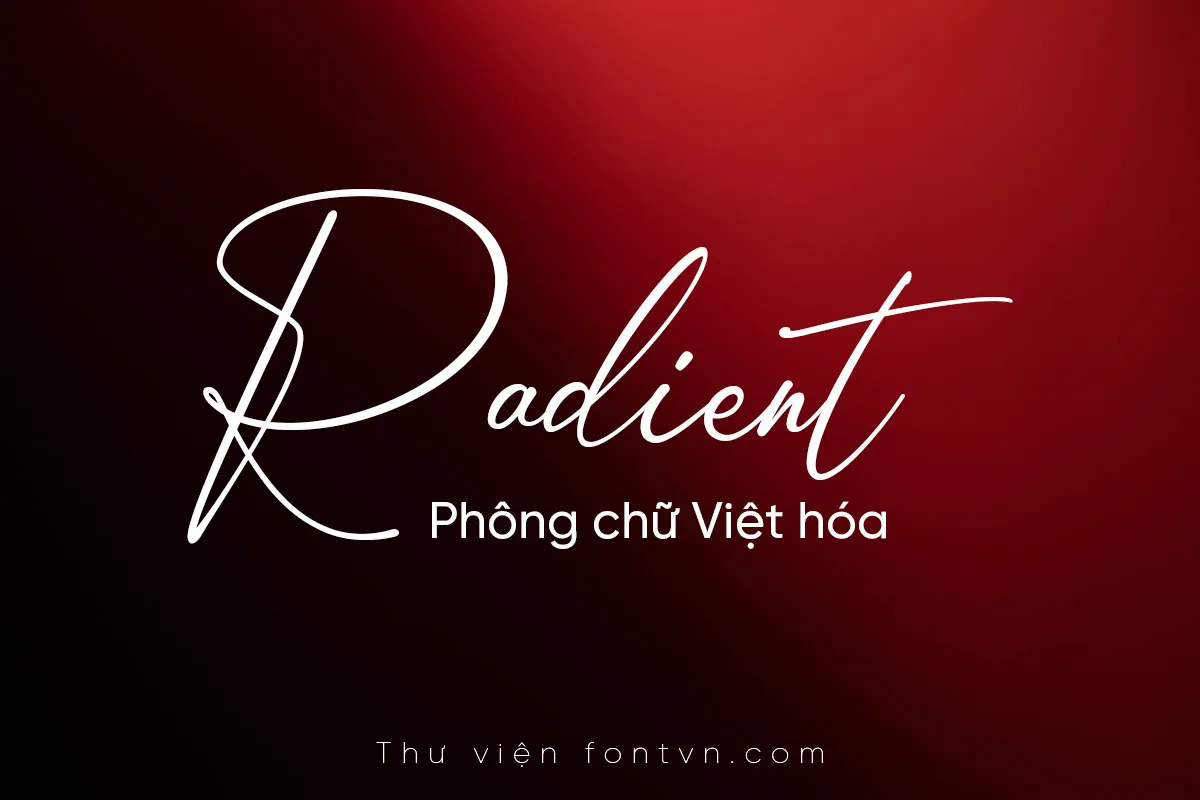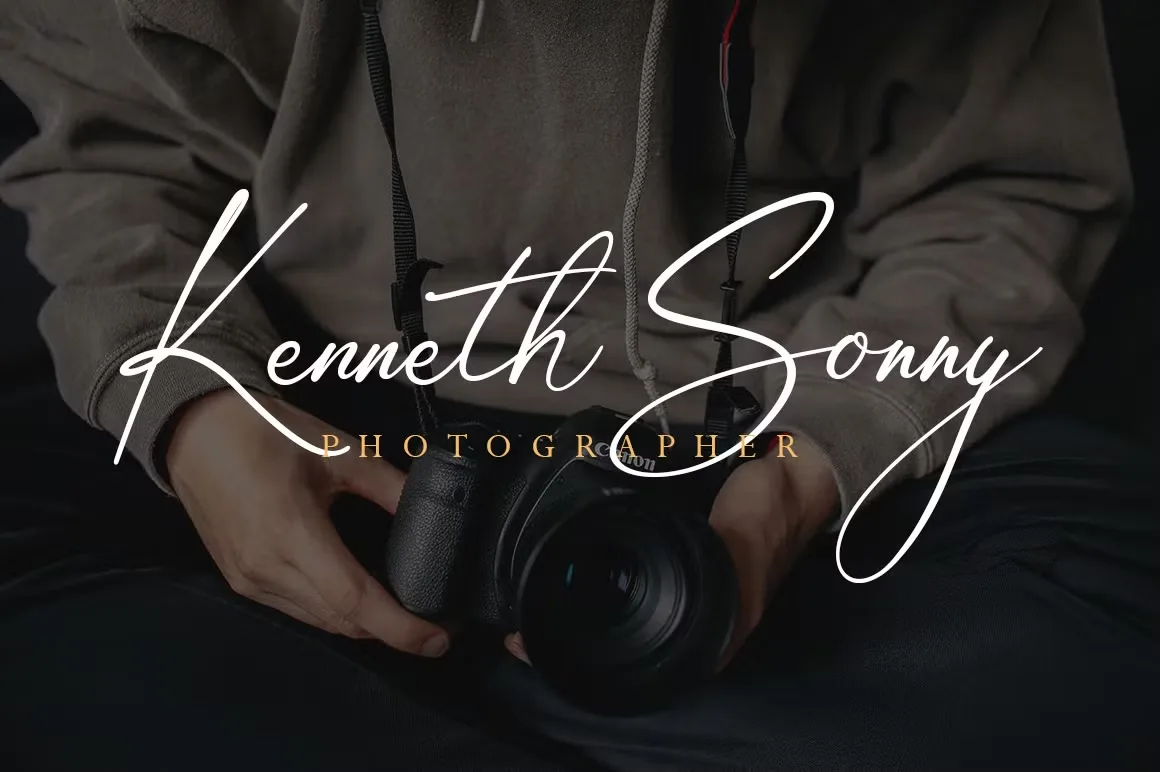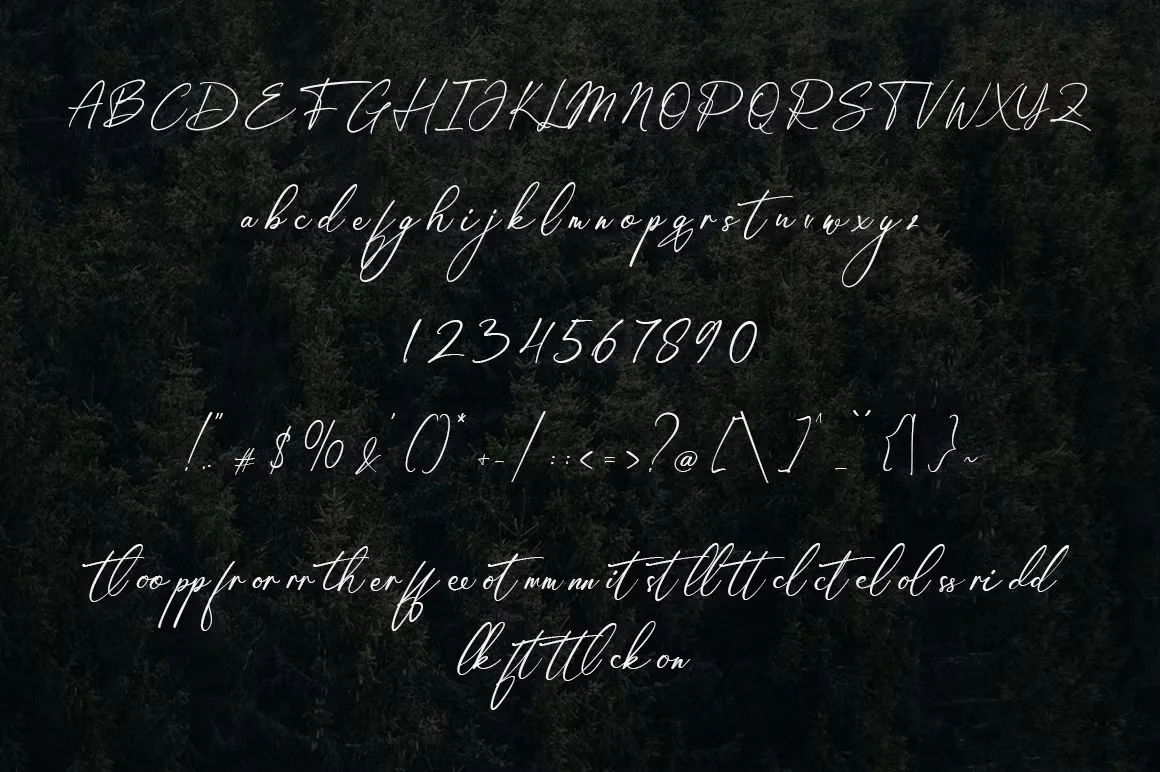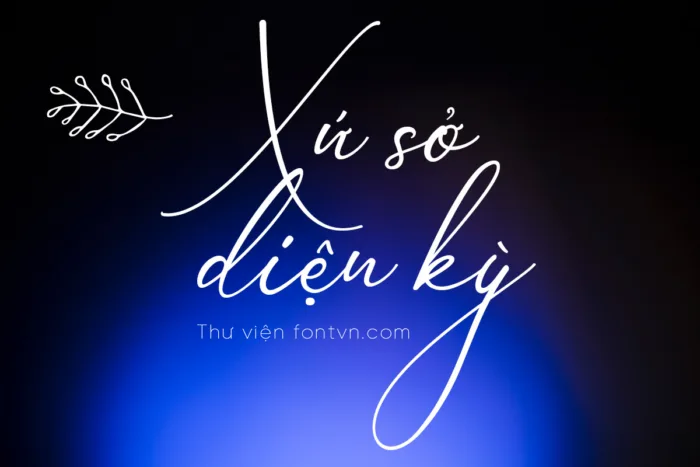
DVN Amsterdam Handwriting Việt hóa – Font chữ ký tuyệt đẹp cho mọi thiết kế
DVN Amsterdam Handwriting Việt hóa là font chữ viết tay mang phong cách chữ ký hiện đại, với nét bút mảnh, liền mạch và uyển chuyển tự nhiên. Các ký tự có độ bay cao, đường nối mềm mại, tạo cảm giác cá nhân, thanh lịch và rất “thật tay”.
Font đặc biệt phù hợp cho thiết kế logo cá nhân, branding, tiêu đề thời trang, mỹ phẩm, thiệp cưới, postcard, chữ ký hình ảnh hoặc các ấn phẩm cần sự tinh tế và cảm xúc. Phần chữ hoa nổi bật, kéo dài đẹp mắt, giúp tổng thể thiết kế trở nên sang trọng và cuốn hút.
DVN Amsterdam Handwriting đã được Việt hóa đầy đủ, hiển thị tiếng Việt mượt mà và dễ đọc, đảm bảo tính thẩm mỹ khi sử dụng trong cả thiết kế số lẫn in ấn chuyên nghiệp.